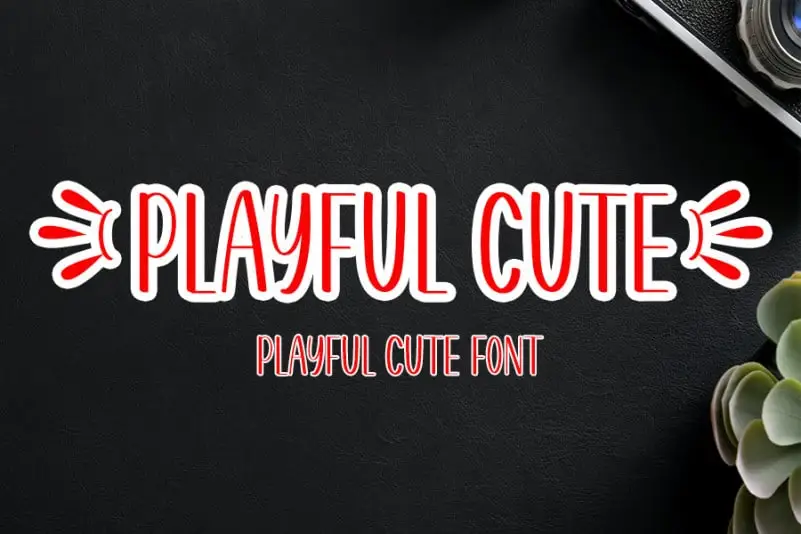
A Playful Cute Display Font é uma elegante tipografia que manterá seu estilo tradicional chamigrafico ao mesmo tempo que apresenta um toque contemporâneo e atual. Esta fonte pode ser facilmente adaptada para uma variedade de ideias criativas, desde cartazes e títulos até impressão em papel de carta. Suas linhas delicadas e cores suaves certamente vão se destacar nos seus projetos, oferecendo uma maneira divertida e alegre de tornar qualquer texto memorable. Ideal para aqueles que querem um visual acolhedor com um toque inovador, esta fonte é uma excelente opção para designers gráficos em busca de algo novo e vibrante.